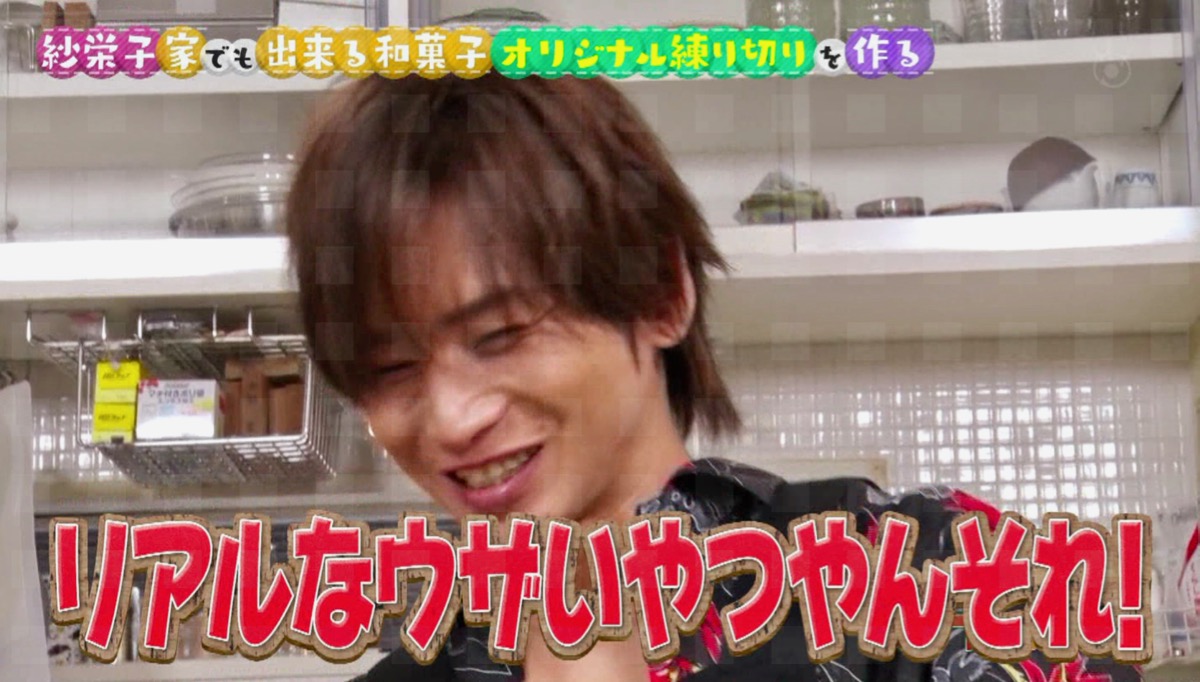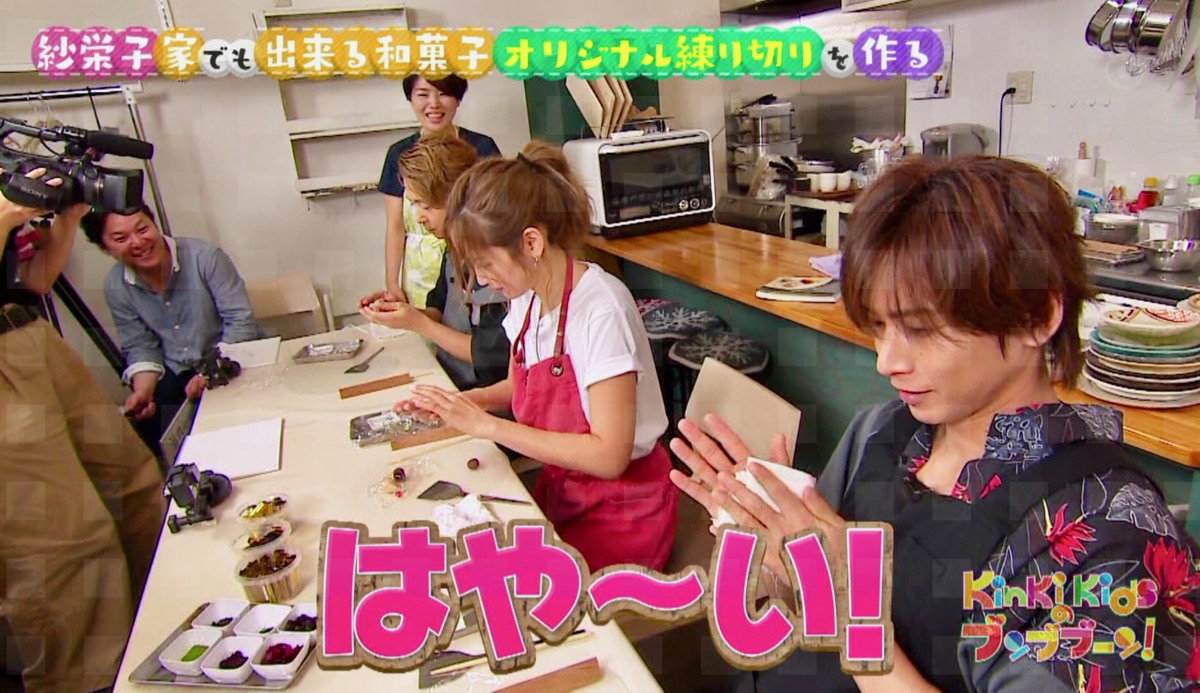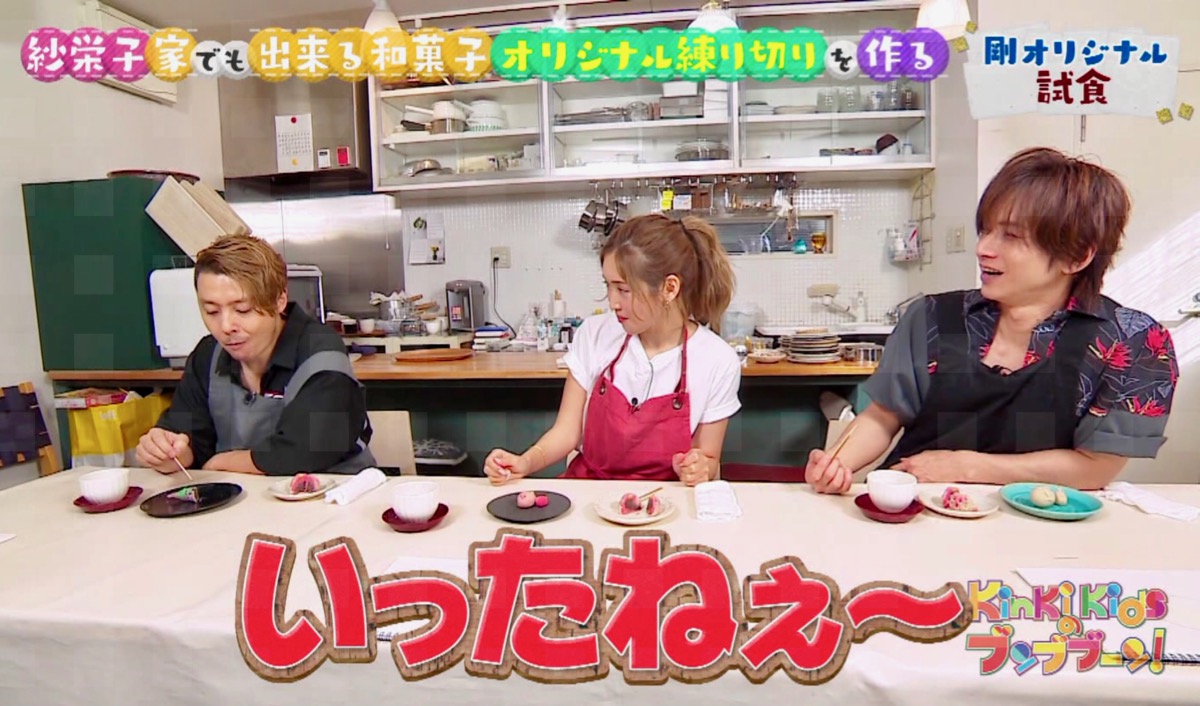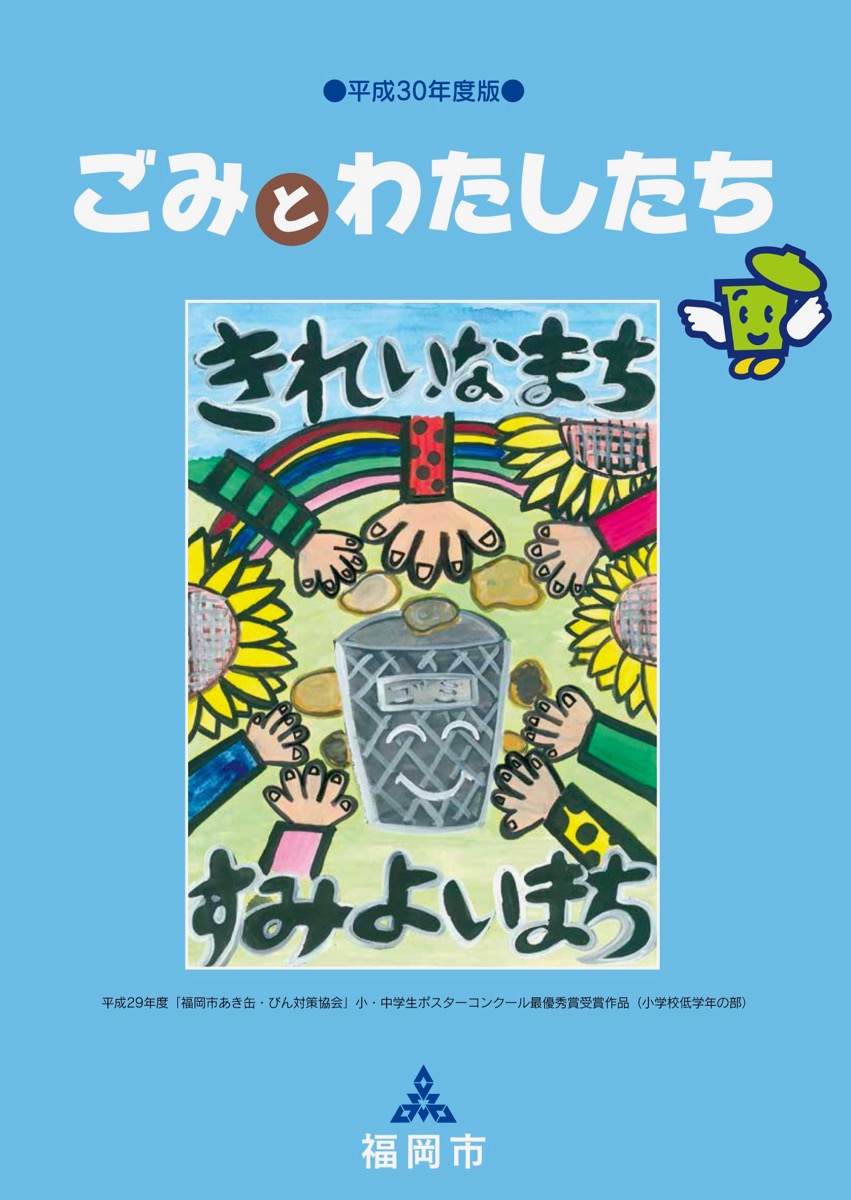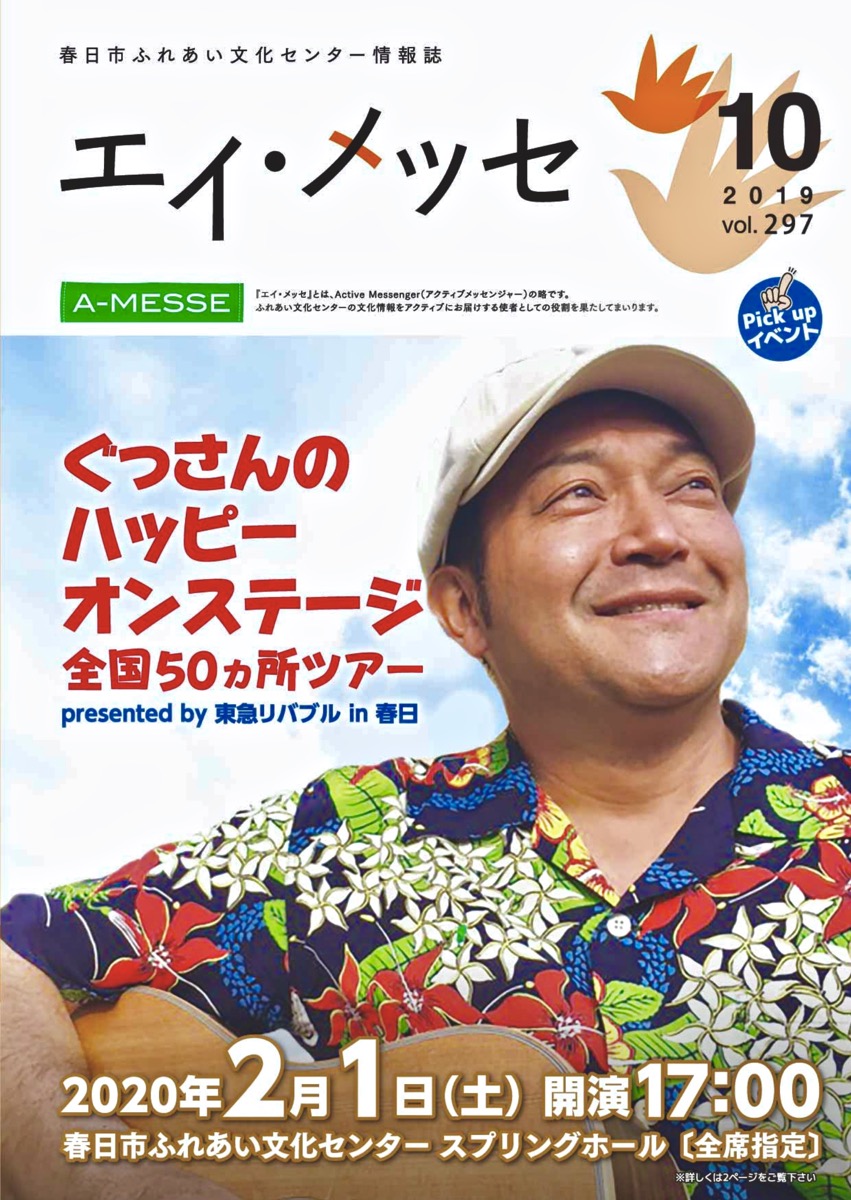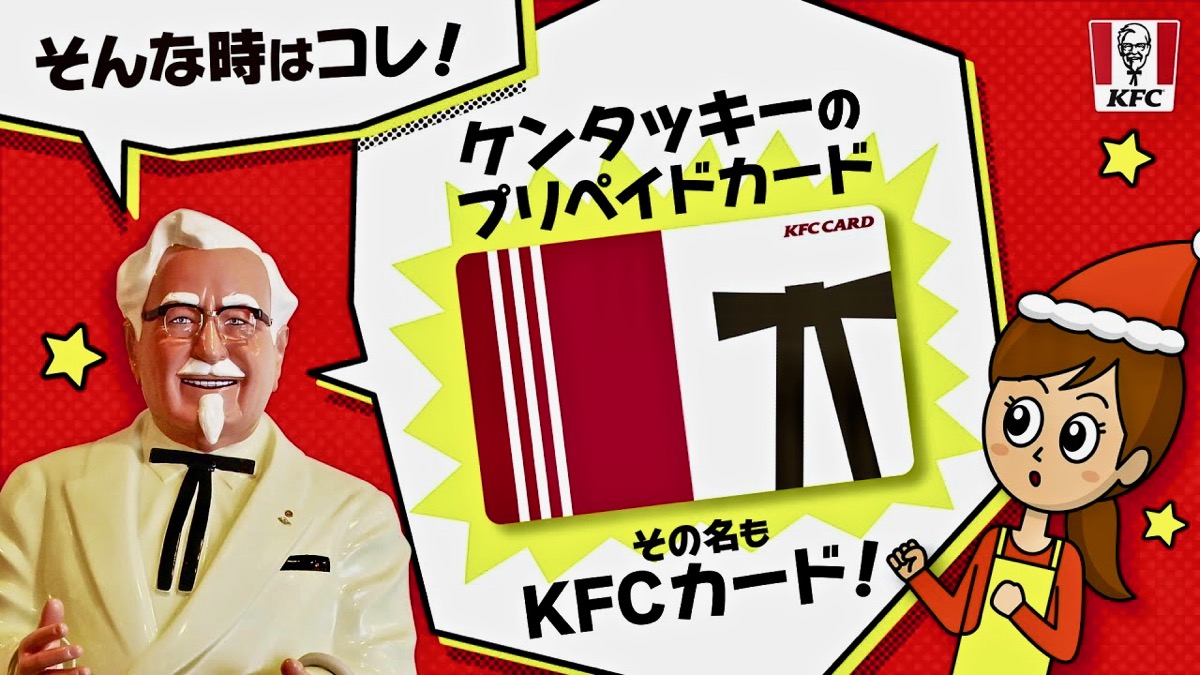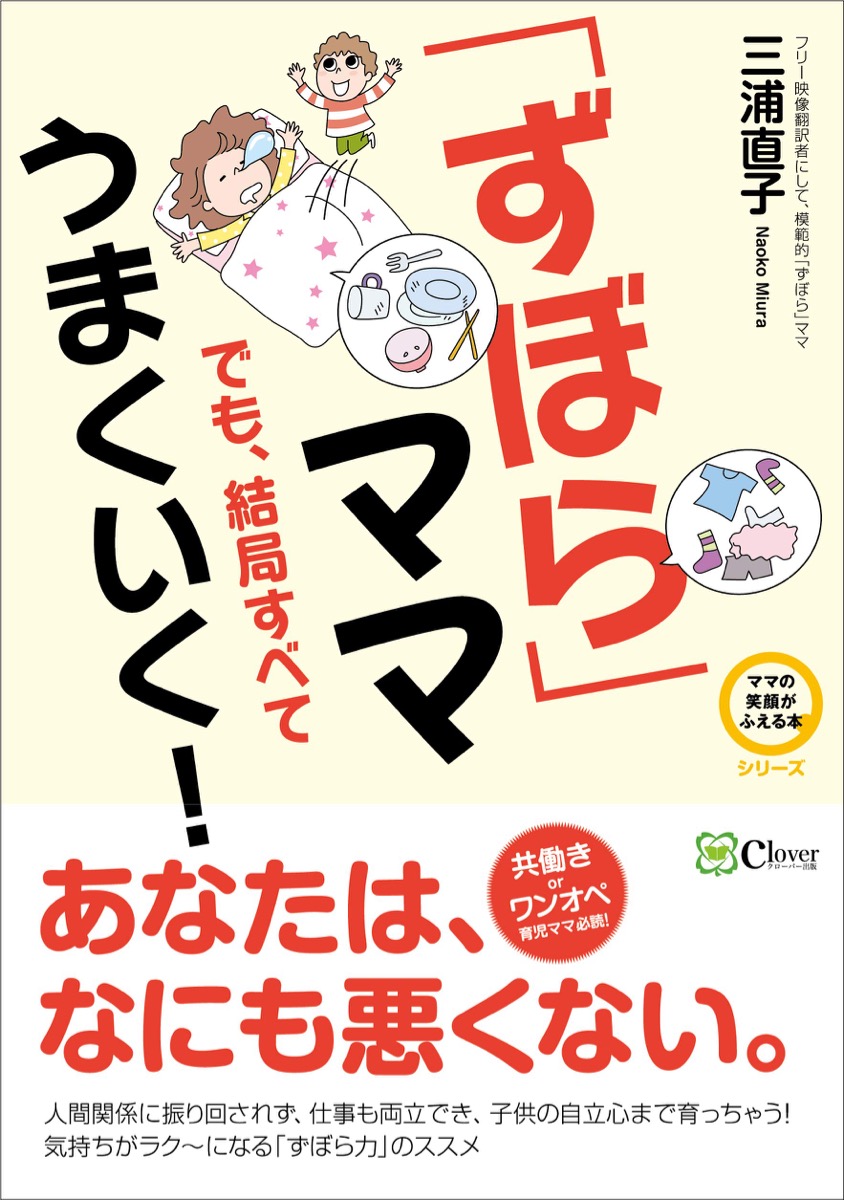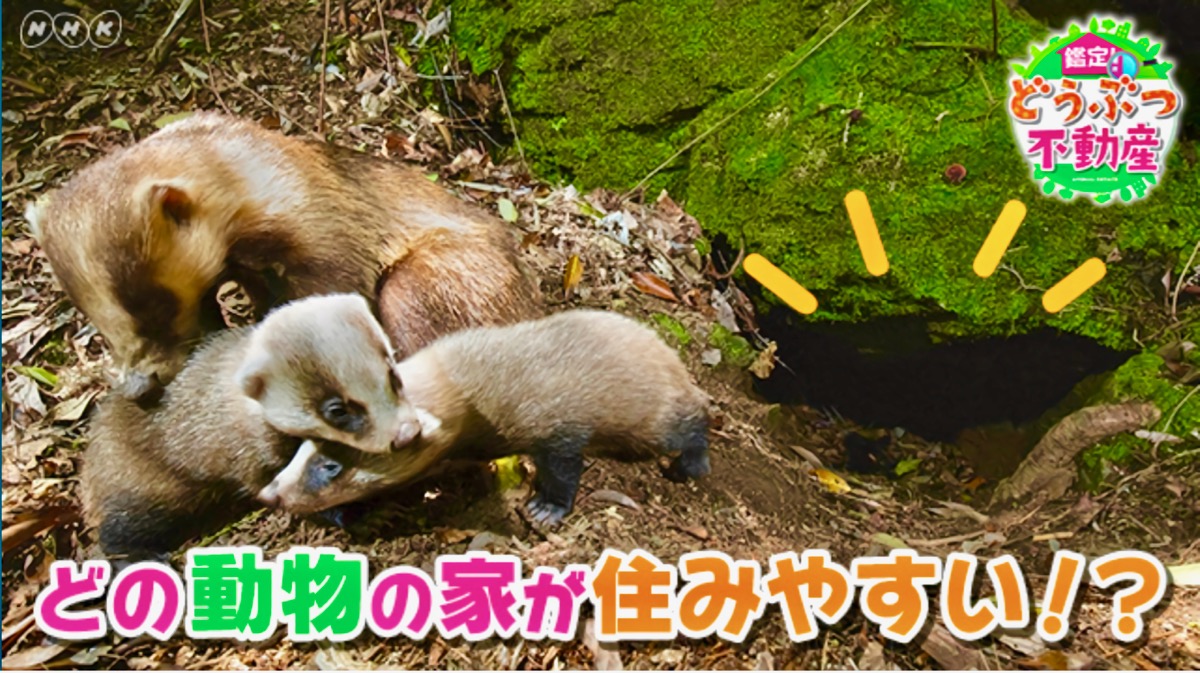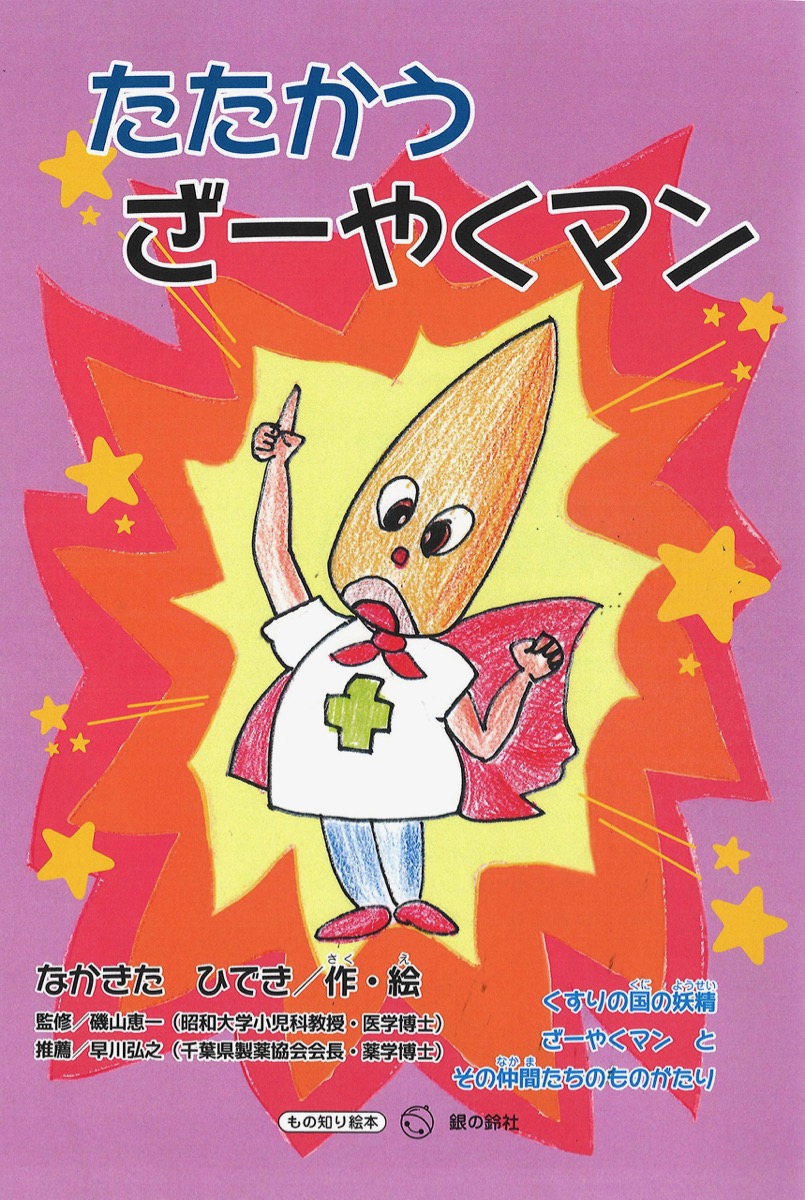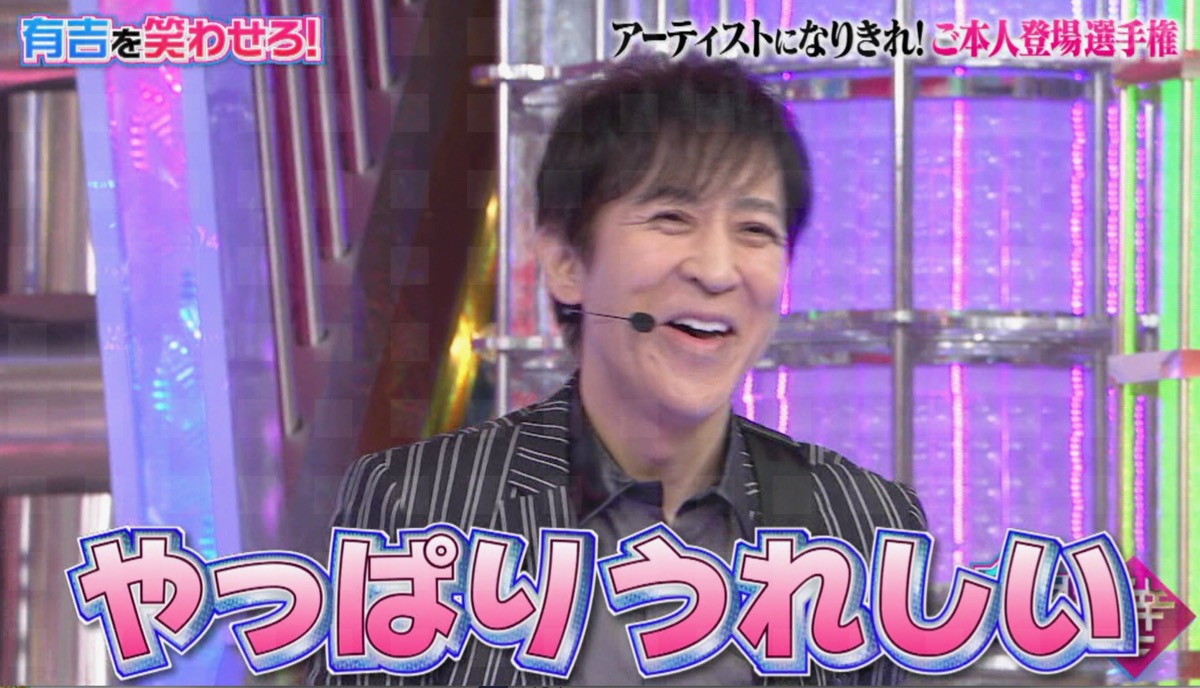
テレビ番組 さとうゆたか
日本テレビ「メレンゲの気持ち」。
本の表紙 さとうゆたか
書名:みんなにいいおかお
著者:木村裕一、ふくざわゆみこ
発行:ポプラ社
もう1点。
書名:ぼくもできるよ!
著者:木村裕一、ふくざわゆみこ
発行:ポプラ社
これも…。
書名:せかいいちのおべんとう
著者:木村裕一、ふくざわゆみこ
発行:ポプラ社
本の表紙 さとうゆたか
書名:カチコチとけい(ミキハウスの絵本)
著者:さつきねむ、わだことみ
発行:三起商行
テレビ番組 さとうゆたか
テレビ朝日、世界の村で発見!こんなところに日本人。
もうひとつ…。
本の表紙 さとうゆたか
書名:新敬語「マジヤバイっす」
著者:中村 桃子
発行:白澤社
本の表紙 さとうゆたか
書名:チリメンモンスターのひみつ
著者:いずもりよう、きしわだ自然資料館
発行:偕成社
本の表紙 さとうゆたか
書名:料理がひらめくワークブック
著者:長野 照明
発行:Amazon Services International, Inc.
テレビ番組 さとうゆたか
テレビ朝日系列のスーパーJチャンネル。
本の表紙 さとうゆたか
書名:うしこのひみちゅ
著者:曽根麻矢
発行:秋水社ORIGINAL
ピーヤの休日(YouTubeチャンネル) takumi
小島よしおによるYouTubeチャンネル「ピーヤの休日」の動画で「ハッピールイカ」書体がたくさん使われています。
ウェイトは一番太い09でしょうか。
参考にもう1枚。
特徴的な「1」もそうですが、「」や『』のデザインとか、半濁点「゜」の大きさや付け方からも他社にライセンスされているハッピー書体と違う「ハッピールイカ」だと判別できますね。
ハッピールイカの雰囲気は、小島よしおの芸にピッタリな感じです。
タイプラボのフォントは、youtuberたちに好まれていますね。